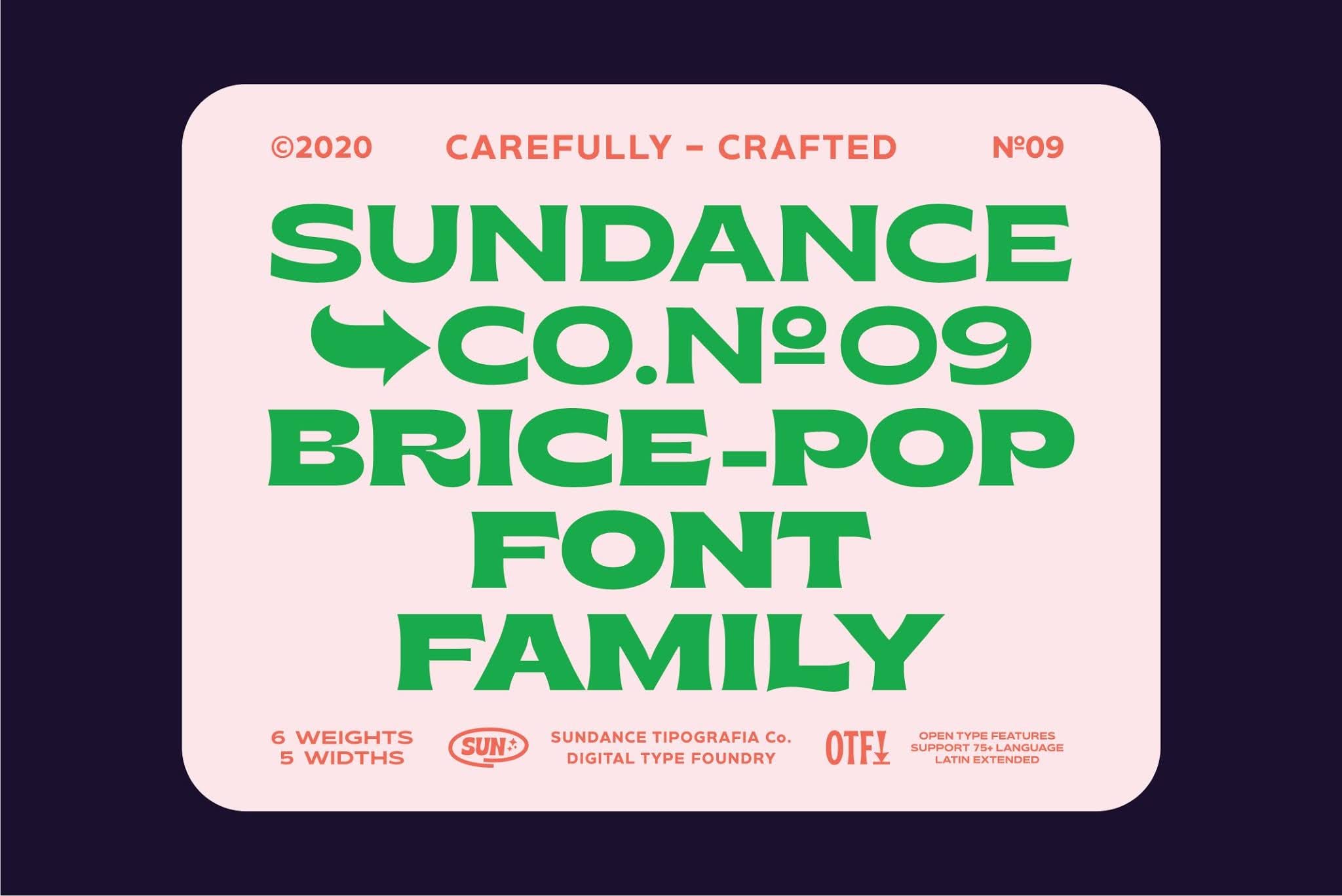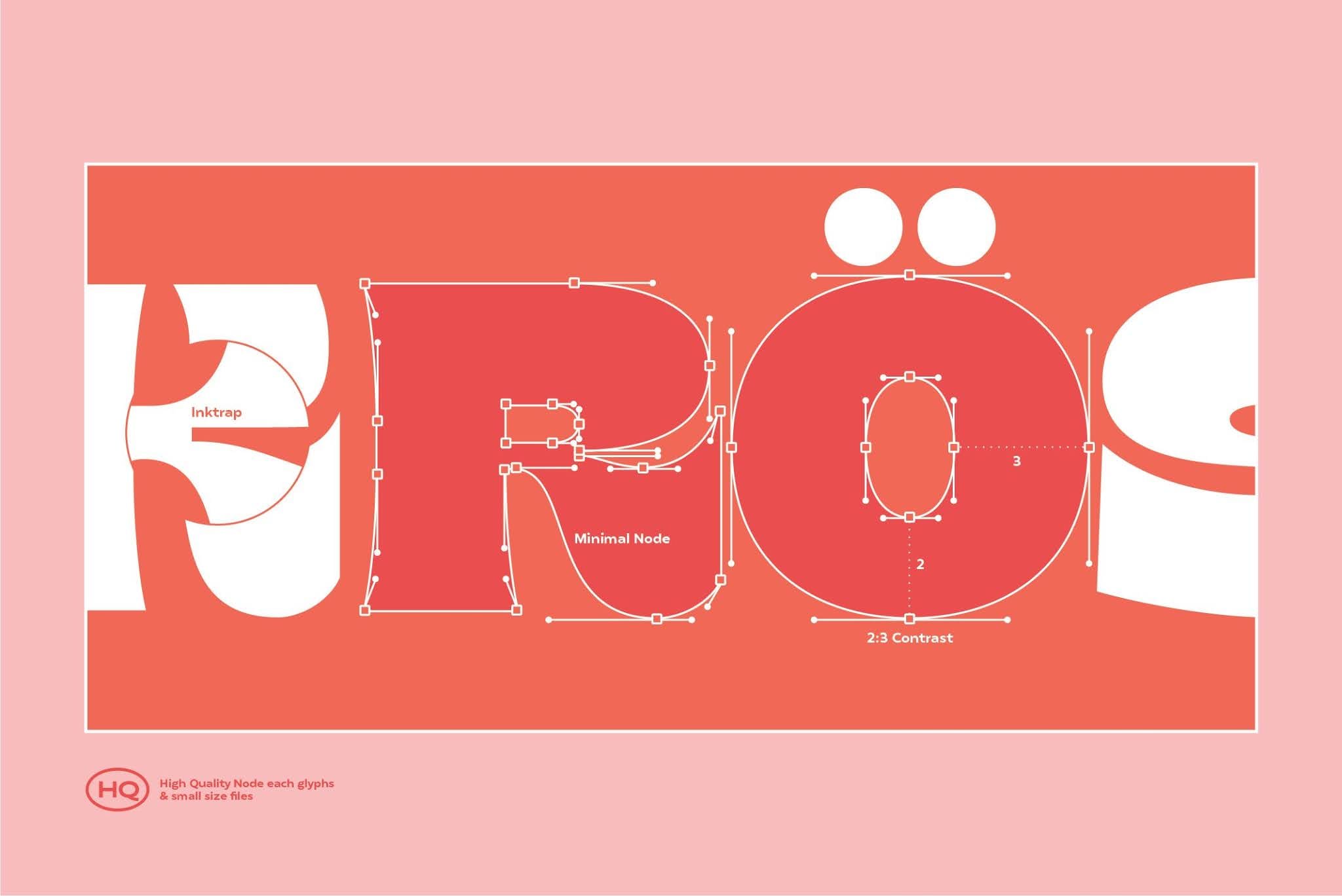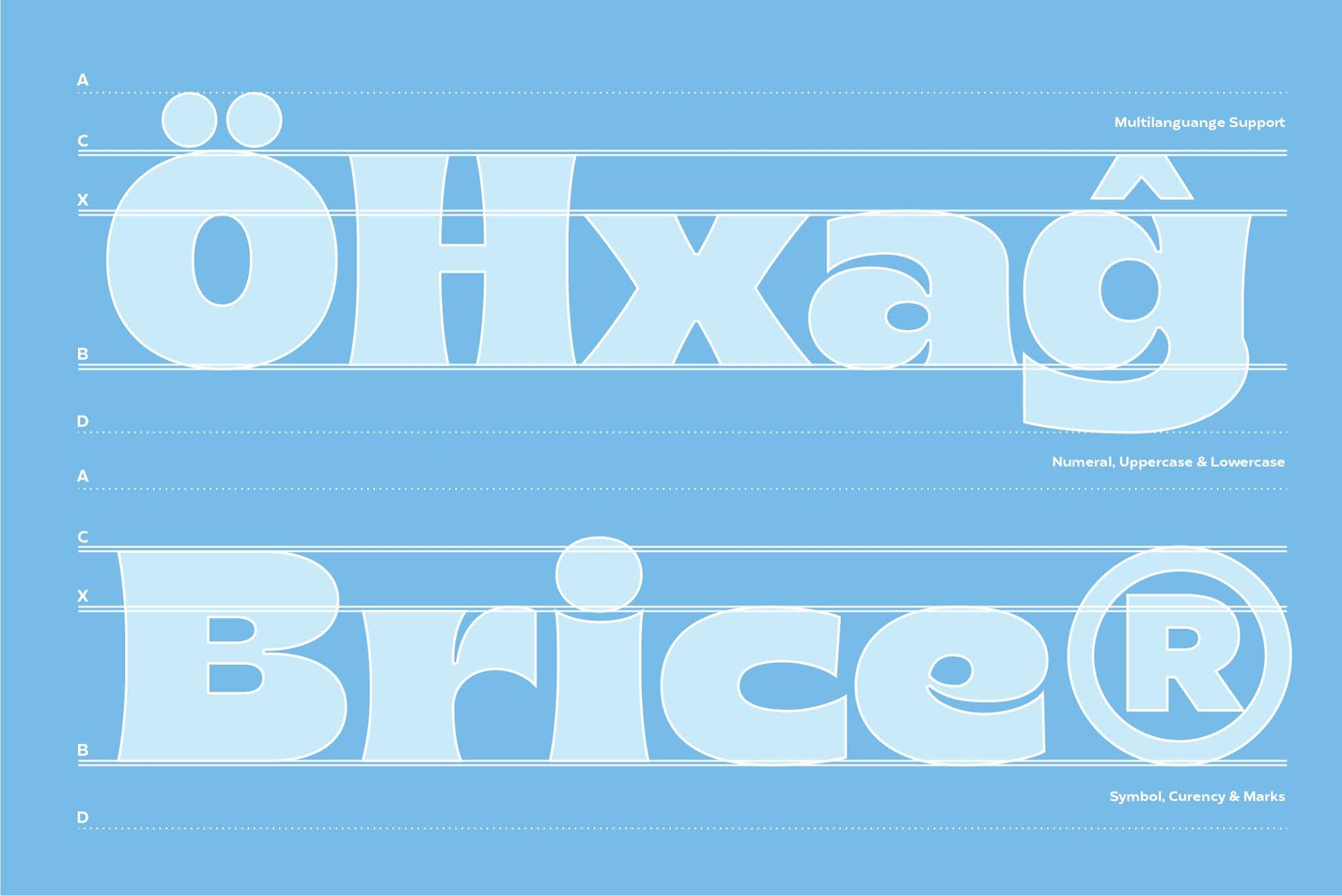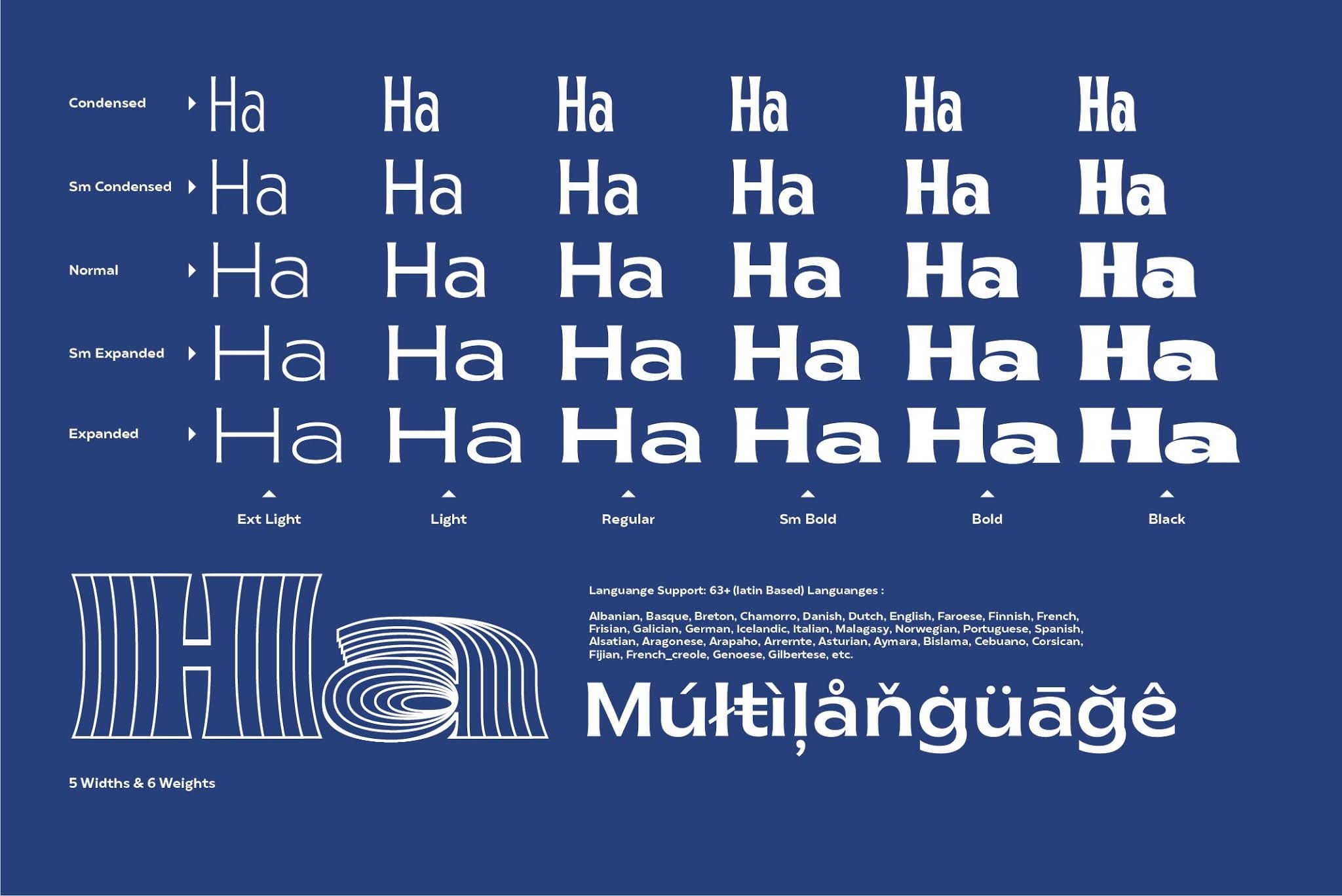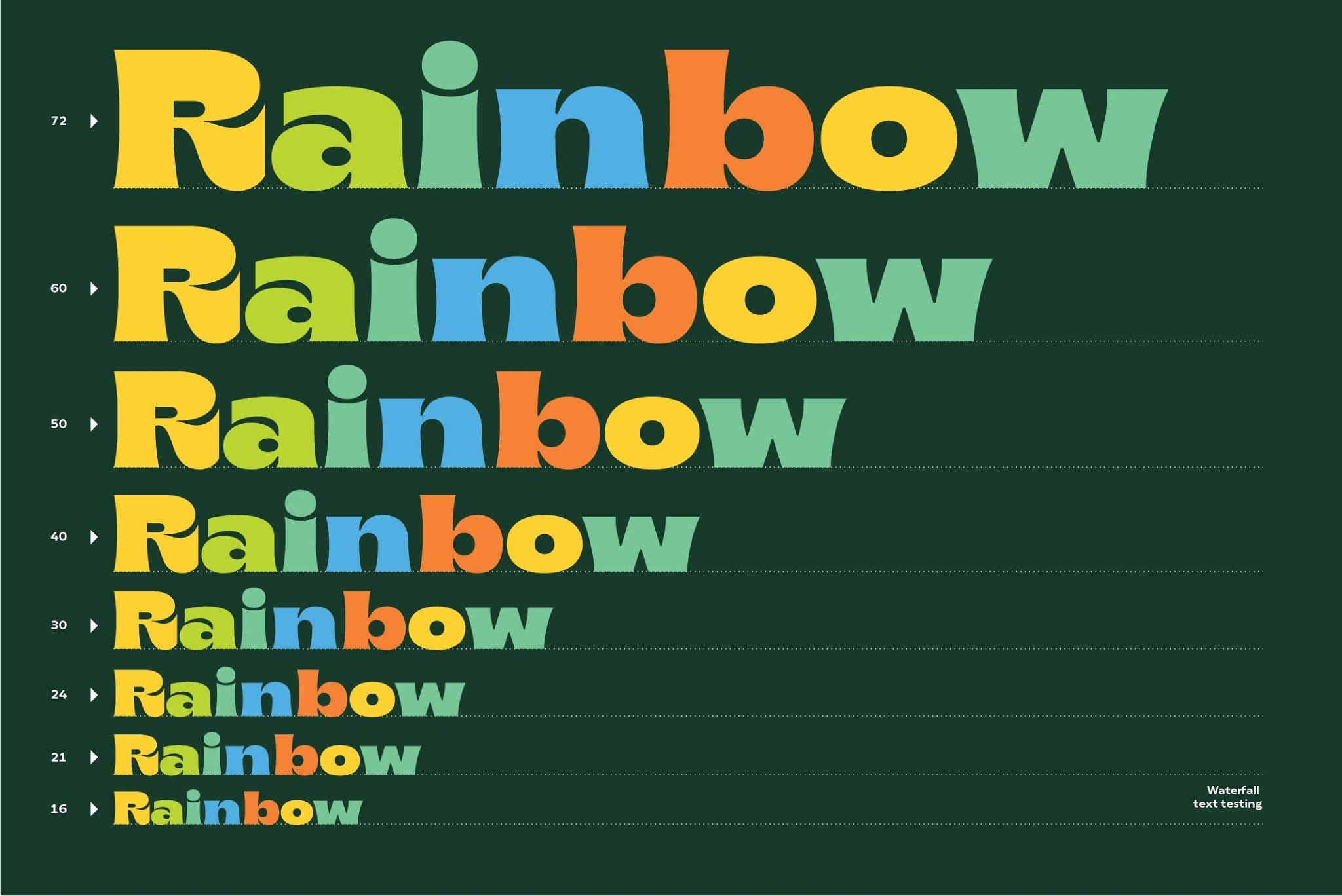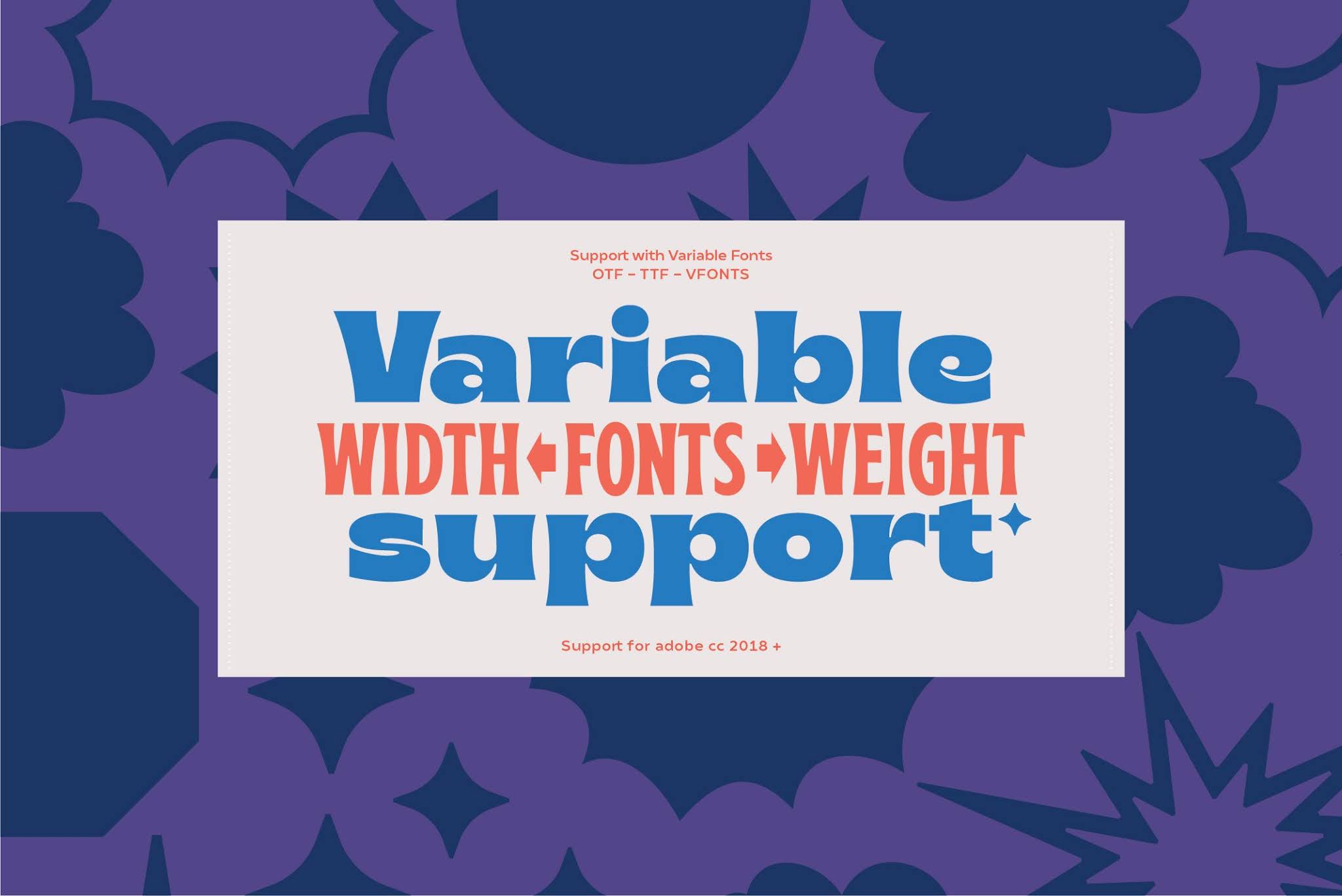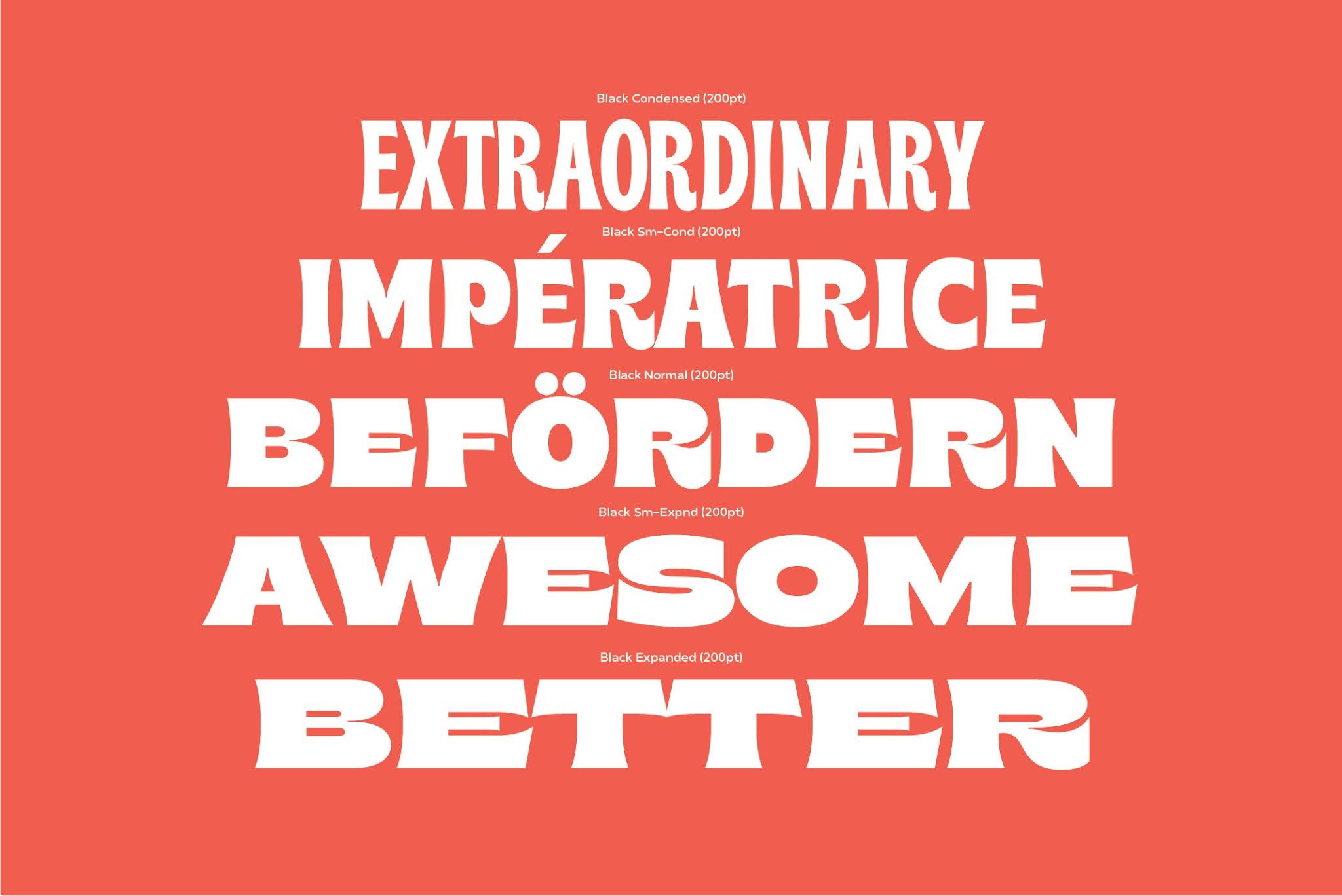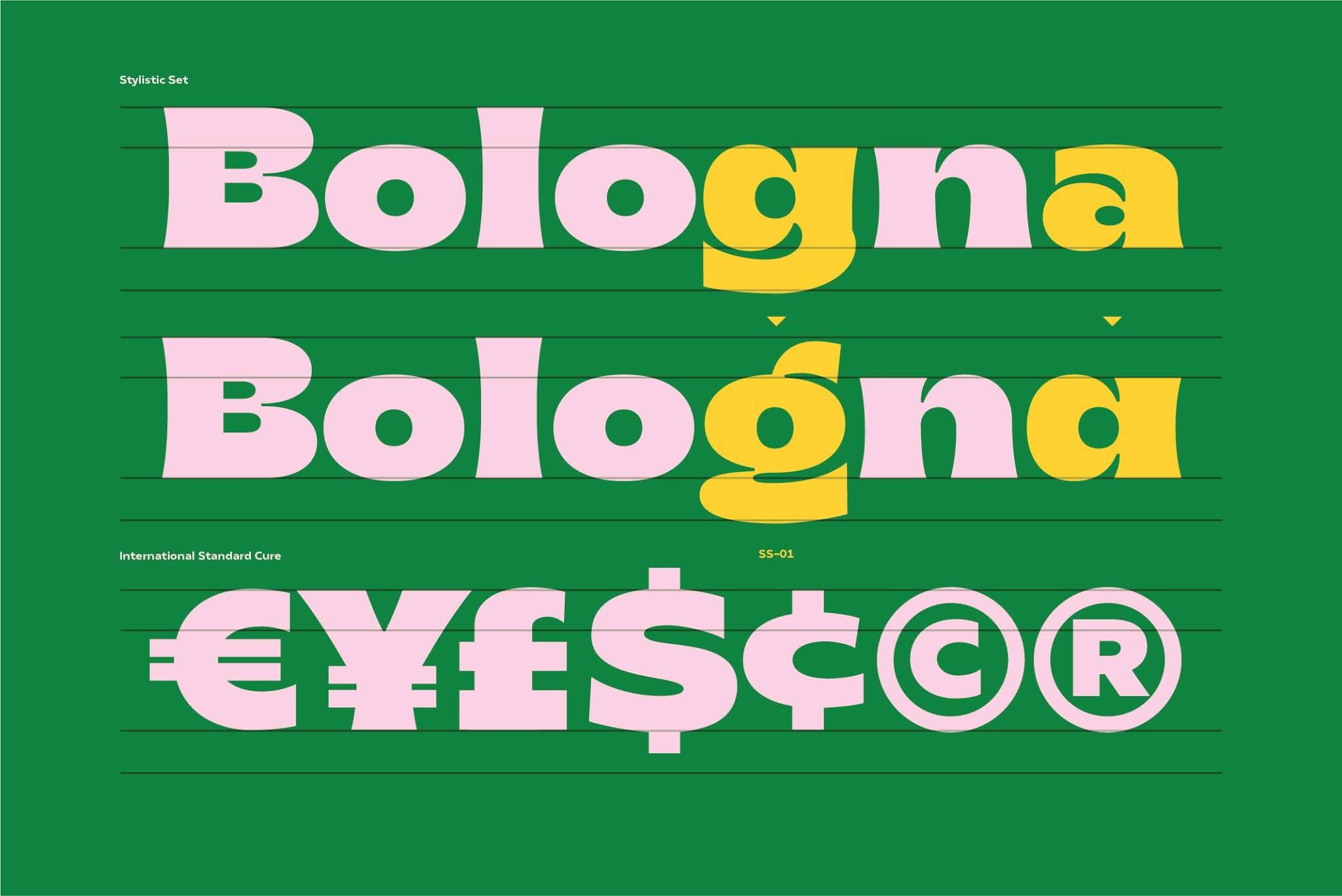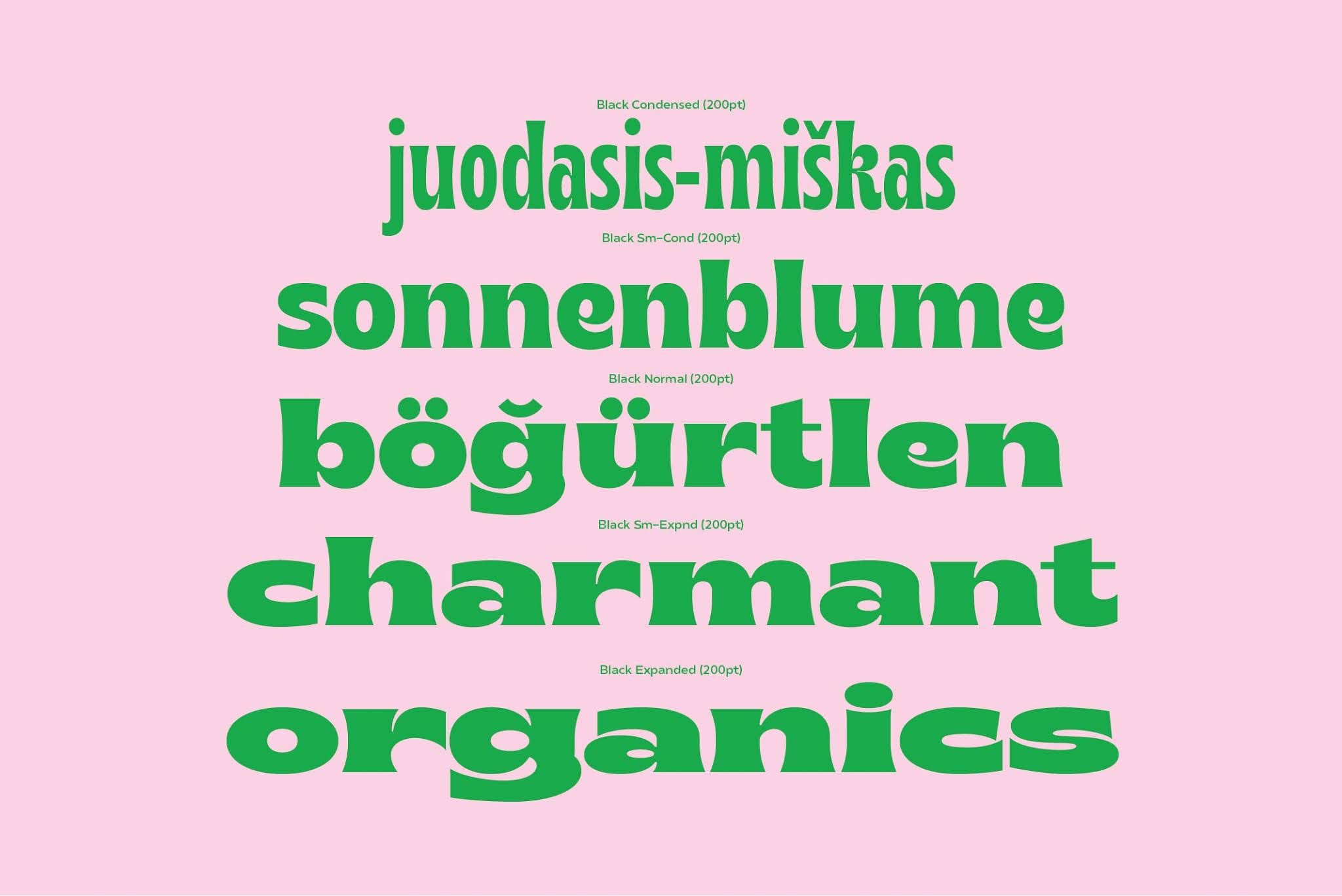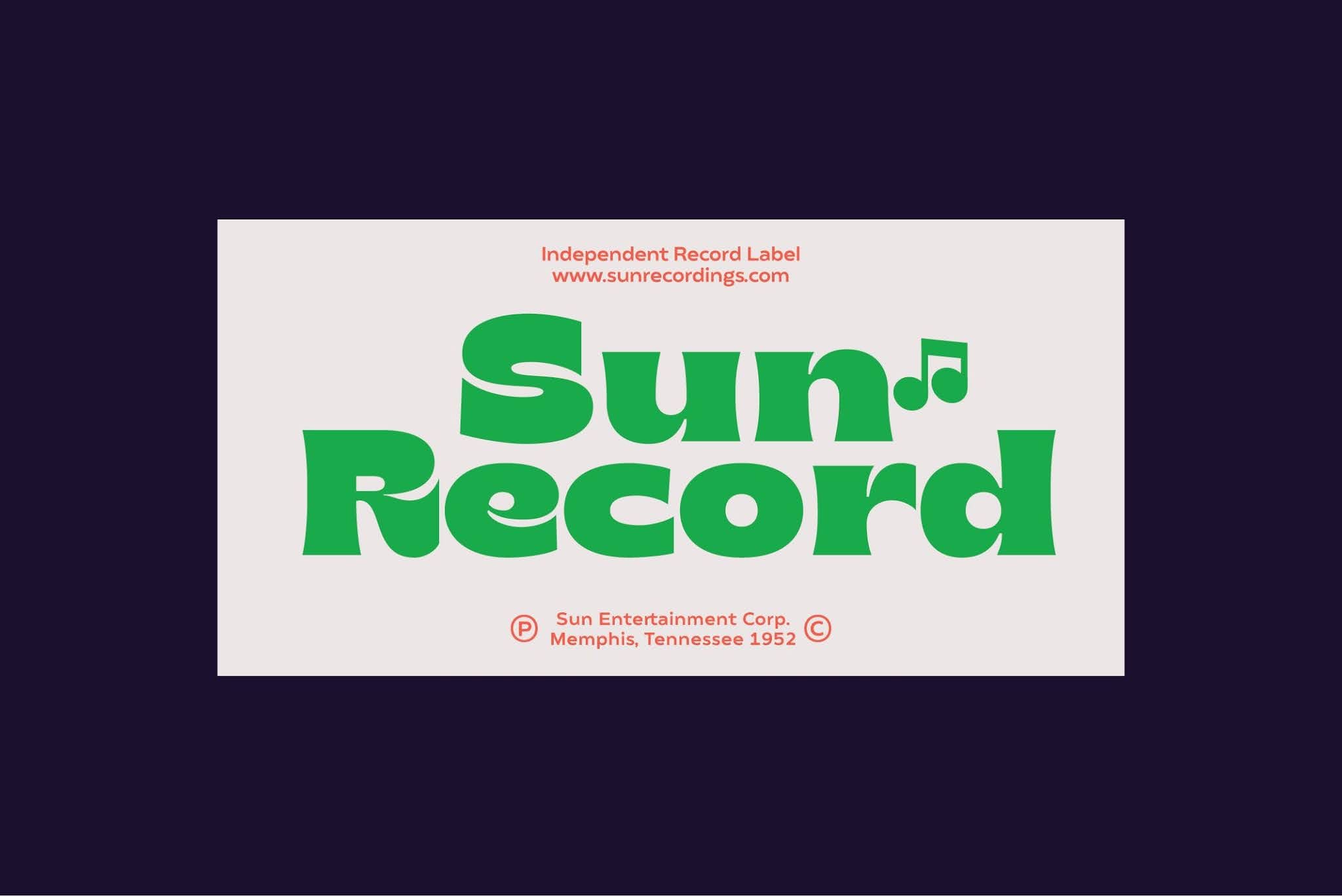
Brice mang thiết kế độc đáo đề cập đến các sản phẩm văn hóa của những năm 80 như âm nhạc, nghệ thuật, văn học, thời trang, khiêu vũ, phim ảnh.
Đặc điểm của Brice là ở serif nhỏ có độ tương phản động, như R, B, S, K, P, v.v. Hoàn hảo cho hầu hết các thiết kế.
Brice có sẵn trong 5 width (Condensed – SemiCondensed – Normal – SemiExpanded – Expanded) với các trận đấu 6 weight (ExtraLight – Normal – SemiBold – Bold – Black) và hỗ trợ hơn 75 ngôn ngữ.